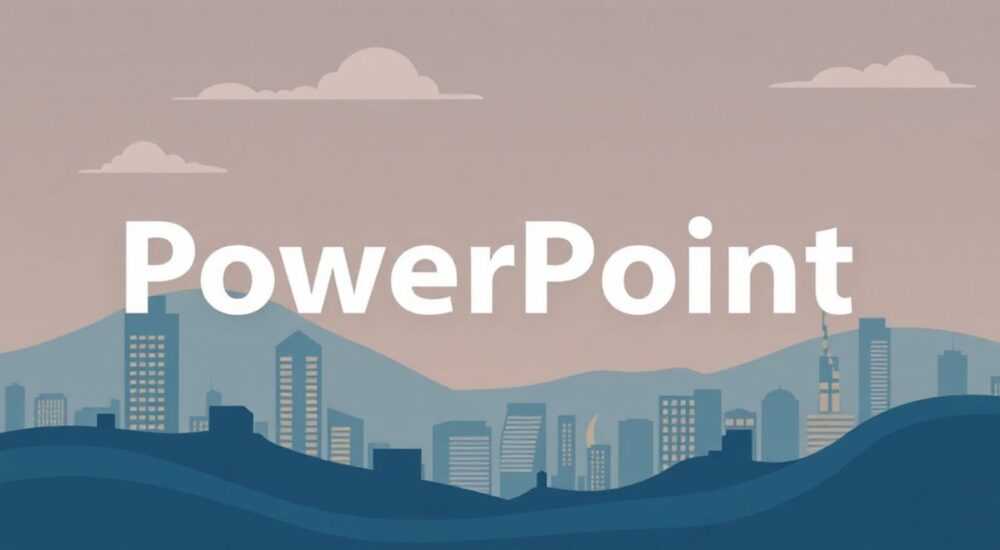
Какой шрифт используется в презентациях powerpoint
В современных презентациях шрифт играет ключевую роль: он определяет читаемость, восприятие информации и общее впечатление от выступления. Microsoft PowerPoint, как один из самых популярных инструментов для создания слайдов, по умолчанию использует шрифт Calibri — универсальный беззасечковый шрифт, разработанный специально для экранного отображения. Однако с 2023 года компания Microsoft объявила о глобальном обновлении стандартного шрифта во всех приложениях пакета Office, включая PowerPoint.
Какой шрифт используется по умолчанию в PowerPoint
До 2023 года стандартным шрифтом во всех версиях PowerPoint был Calibri — современный, чистый, легко читаемый шрифт без засечек. Он был представлен в 2007 году вместе с выходом Office 2007 и быстро стал символом цифровой корпоративной эпохи. Calibri разработан командой Lucas de Groot специально для экранов, с акцентом на комфорт при длительном чтении.
Однако с 2023 года Microsoft официально заменила Calibri на новый шрифт под названием Aptos (до этого известный как Bierstadt). Это решение стало частью масштабного редизайна всего офисного пакета, направленного на повышение доступности, читаемости и визуальной ясности.
Aptos отличается более высокими пропорциями букв, увеличенными межбуквенными интервалами и улучшенной различимостью символов. Например, строчные «l» и заглавная «I» теперь легко различимы, что было частой проблемой в Calibri. Это особенно важно при демонстрации данных, где точность имеет значение.
Microsoft провела масштабное исследование среди пользователей, протестировав пять финалистов: Grandview, Seaford, Skeena, Tenorite и Bierstadt (Aptos). По результатам тестирования именно Aptos показал лучшую читаемость на разных устройствах и размерах экранов.
Почему Microsoft выбрала Aptos вместо Calibri
Решение о смене шрифта было продиктовано не только эстетическими предпочтениями, но и реальными потребностями современных пользователей. Средний пользователь сегодня работает на множестве устройств: от больших дисплеев до планшетов и проекторов в конференц-залах. Calibri, созданный в 2007 году, начал терять свои преимущества на фоне новых технологий.
Aptos — это ответ на вызовы времени. Шрифт разработан с учётом принципов инклюзивного дизайна: он лучше воспринимается людьми с нарушениями зрения, а также обеспечивает высокую контрастность и чёткость даже при маленьком кегле. Буквы имеют более открытые формы, что снижает зрительную усталость.
Кроме того, Aptos поддерживает широкий диапазон языков и символов, включая кириллицу, латиницу, греческий и коптский алфавиты. Это делает его идеальным выбором для международных компаний и многоязычных презентаций.
Параметр |
Calibri |
Aptos |
Год выпуска |
2007 |
2023 |
Тип шрифта |
Беззасечковый |
Читаемость на экране |
Очень высокая |
Различимость l/I/1 |
Низкая |
Поддержка кириллицы |
Языкозависимые альтернативы |
Segoe UI (для некоторых локализаций) |
Segoe UI (резерв) |
Лучшие шрифты для презентаций: критерии выбора
Хотя Aptos — официальный стандарт, вы не обязаны ограничиваться им. В зависимости от темы, аудитории и формата выступления можно использовать другие шрифты. Главное — соблюдать базовые правила типографики.
Первое правило: читаемость важнее стиля. Даже самый красивый шрифт бесполезен, если его трудно прочесть с задних рядов зала. Поэтому беззасечковые шрифты (sans-serif) остаются золотым стандартом для презентаций.
Второе: универсальность. Используйте шрифты, которые есть на большинстве компьютеров, или встраивайте их в файл. Иначе при открытии на другом устройстве шрифт может замениться, исказив дизайн.
Третье: ограничьте количество шрифтов. Один — для заголовков, другой — для основного текста. Три и более — перегрузка. Лучше использовать вариации одного семейства: жирный, курсив, светлый.
- Aptos — новый стандарт Microsoft, идеален для деловых и технических презентаций.
- Segoe UI — родной шрифт Windows, отлично смотрится на экранах, поддерживает все языки.
- Helvetica — легендарный шрифт, символ минимализма. Часто используется в дизайне Apple.
- Roboto — шрифт Google, бесплатный, современный, отлично работает в онлайн-презентациях.
- Open Sans — открытый шрифт с высокой читаемостью, популярен в стартапах и образовательных проектах.
Как изменить шрифт в PowerPoint: пошаговая инструкция
Изменение шрифта — простая задача, но чтобы изменения затронули всю презентацию, нужно работать с образцами слайдов.
- Откройте PowerPoint и перейдите на вкладку Вид.
- Выберите Образец слайдов. Вы увидите главный образец и набор дочерних.